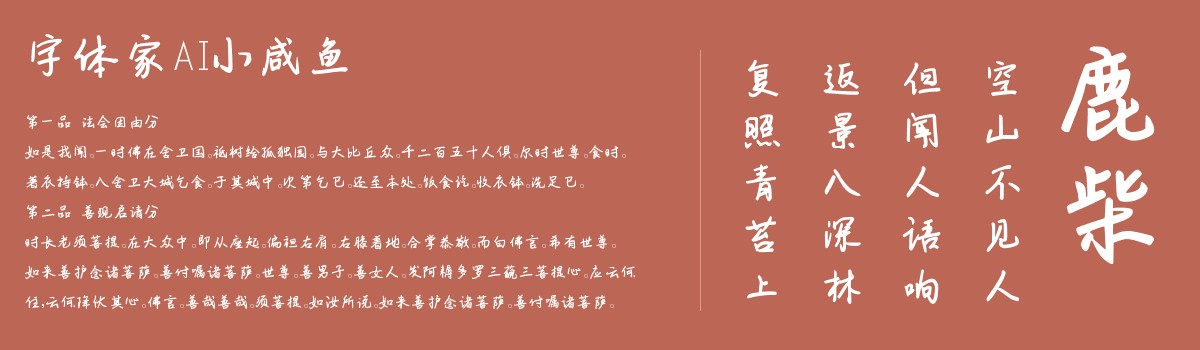
字体家AI小咸鱼
字体家AI小咸鱼是一款由字体家AI神笔造字生成的一款艺术字体,这是一款带有手写温度的字体,似软笔轻书。笔画有自然的粗细变化,起笔收笔如墨色晕染般柔和过渡,非机械均匀线条。线条流畅圆润,拐角处无尖锐棱角,像指尖轻滑纸面的弧度。结构舒展不局促,笔画间有手写特有的微妙呼应,似呼吸般协调。整体质朴无华,无繁复装饰,却透着手写的自然韵律,像冬日暖阳下的随笔,温和亲切,触之可感那份柔软与真诚。比较适合用于艺术类装饰文字,海报、网页、广告设计,室内装饰,平面标题设计、食品包装、品牌标志等。